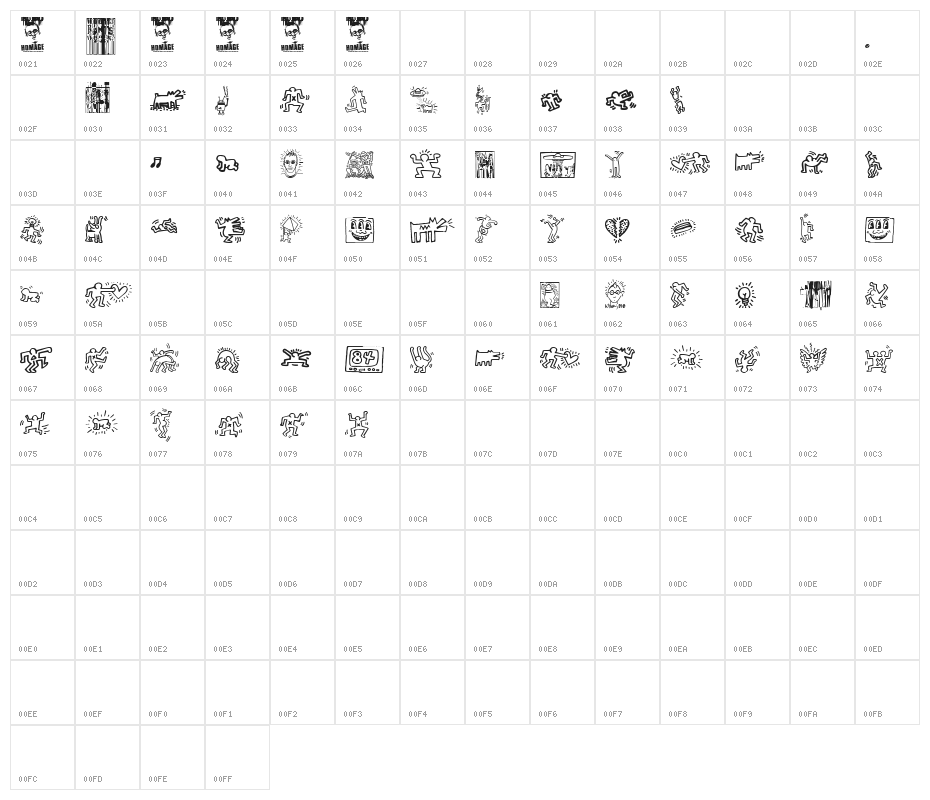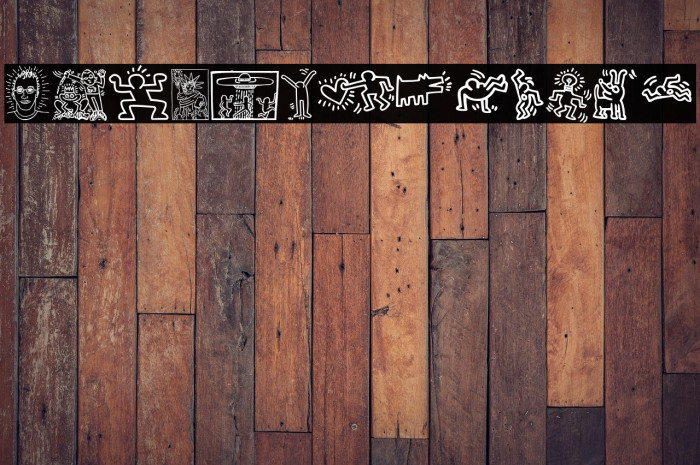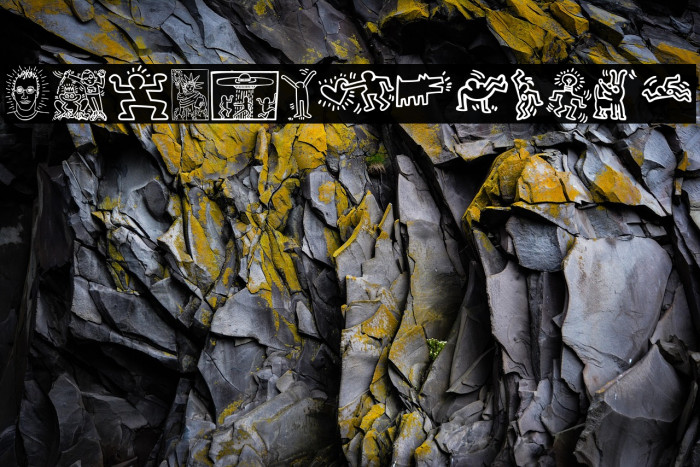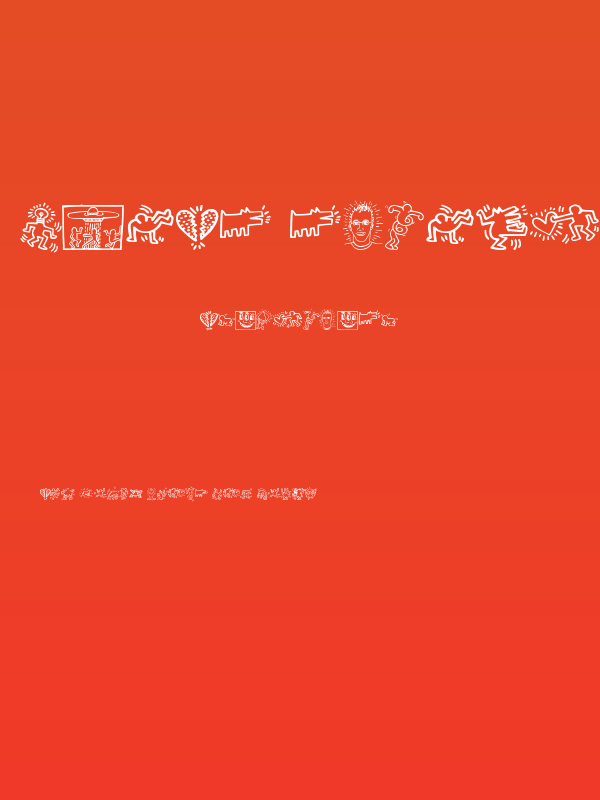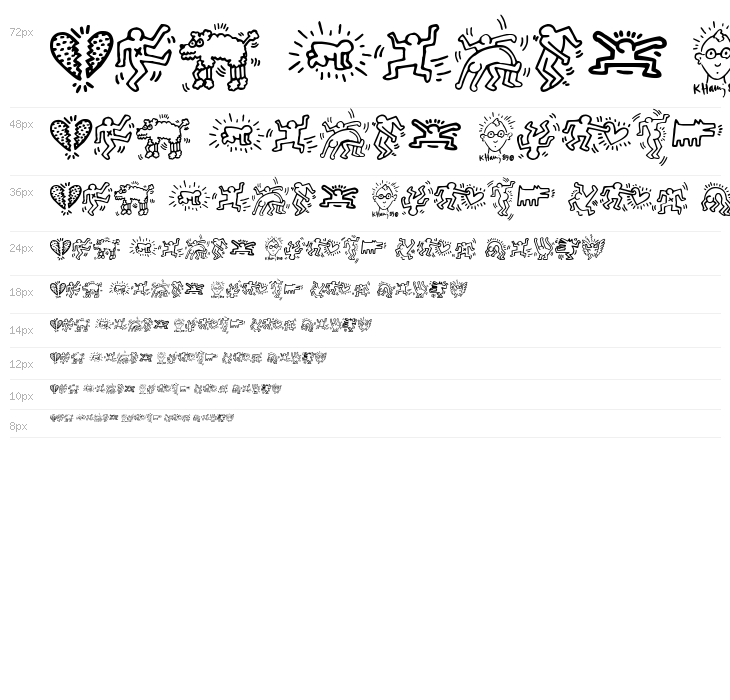
Keith Haring Font
| Stile generale | Decorative, Playful, Urban, Artistic |
| Caso d'uso | Logos, Headlines, Posters, Artistic projects |
| Progetti proposti | Art posters, event flyers, youth-oriented branding, album covers, creative social media graphics. |